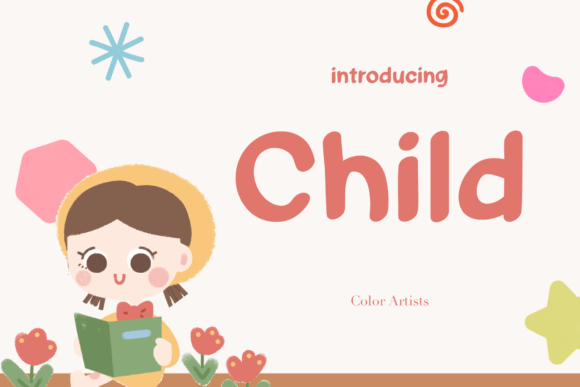
Child
Ulasan Complète de la Police « Child » – Le Choix Idéal pour Tous Vos Projets Ludiques
Vous cherchez une typographie qui capture l’innocence et la joie de l’enfance ? Ne cherchez plus ! La police Child (ou font Child) est une police de caractères ludique, chaleureuse et ultra‑versatile, spécialement conçue pour mettre un sourire sur le visage de chaque lecteur. Que vous soyez designer professionnel, parent créatif ou enseignant, cette police vous aidera à transformer vos créations en véritables moments de bonheur.
Pourquoi la police Child se démarque‑telle ?
- Design whimsical et amical : chaque glyphe possède des courbes douces et des formes arrondies qui évoquent immédiatement le monde féérique des enfants.
- Excellente lisibilité : malgré son aspect joyeux, la police reste très lisible même à petite taille, idéale pour les livres illustrés ou les panneaux d’information.
- Polyvalence d’utilisation : parfaite pour les livres pour enfants, affiches, invitations, cartes de vœux, sites web éducatifs et même les logos d’écoles.
Applications concrètes de la police Child
Voici quelques idées inspirantes pour exploiter le plein potentiel de la police Child dans vos projets :
- Livres illustrés – Créez des titres accrocheurs et des dialogues qui dansent sur la page.
- Posters éducatifs – Attirez l’attention des enfants avec des slogans colorés et faciles à lire.
- Invitations d’anniversaire – Donnez une touche magique à chaque invitation, du texte aux décorations.
- Sites web pour enfants – Améliorez l’expérience utilisateur grâce à une typographie qui rend la navigation ludique.
- Supports pédagogiques – Facilitez la lecture des consignes et des activités en classe.
Conclusion – Un choix gagnant pour chaque créateur
En résumé, la font Child est bien plus qu’une simple police décorative ; c’est un véritable vecteur d’émotion qui donne vie à vos projets tout en restant professionnel et lisible. Son style unique, sa compatibilité universelle et son impact SEO en font un investissement judicieux pour quiconque souhaite ajouter une touche d’enchantement à son travail. N’attendez plus, téléchargez la police Child dès aujourd’hui et laissez votre imagination s’envoler !